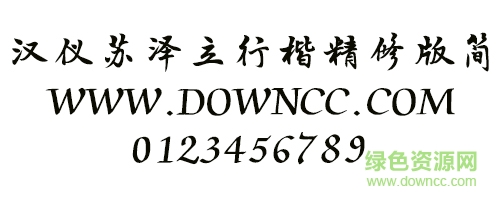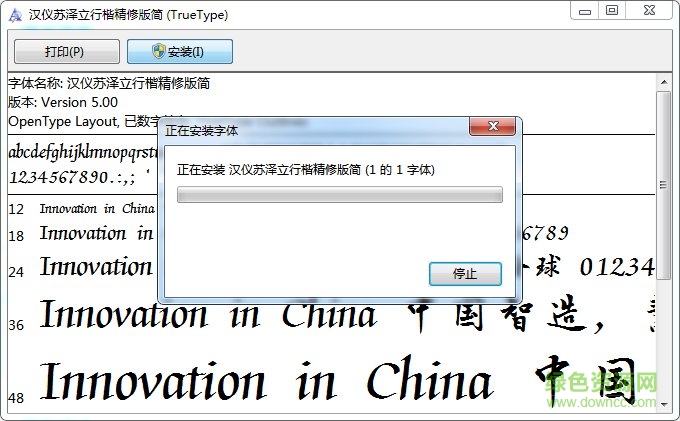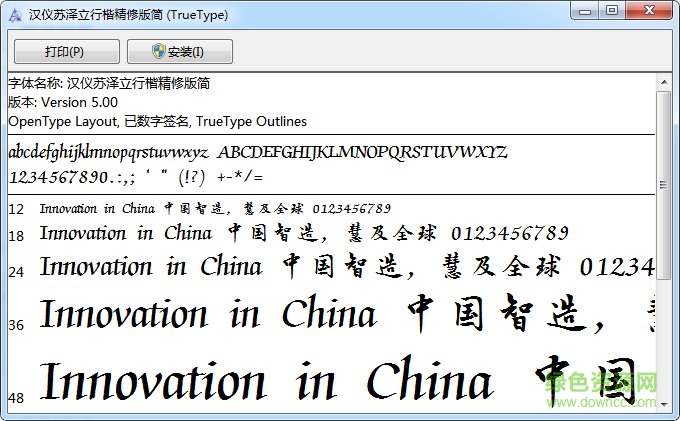
漢儀蘇澤立行楷精修版簡(jiǎn)
漢儀蘇澤立行楷精修版簡(jiǎn)是一個(gè)免費(fèi)字體資源。這款字體在原版基礎(chǔ)上進(jìn)行了修飾,輸出的字體看起來更加美觀!可以用于廣告設(shè)計(jì)、平面設(shè)計(jì)等。喜歡漢儀蘇澤立行楷精修版簡(jiǎn)字體的朋友歡迎下載使用。
漢儀蘇澤立行楷精修版簡(jiǎn)字體
字體風(fēng)格:古典\中國(guó)風(fēng)\手寫風(fēng)\有力\穩(wěn)重
推薦場(chǎng)景:標(biāo)志\導(dǎo)視\廣告\書籍\報(bào)紙\游戲\動(dòng)漫\影視\屏顯\印章